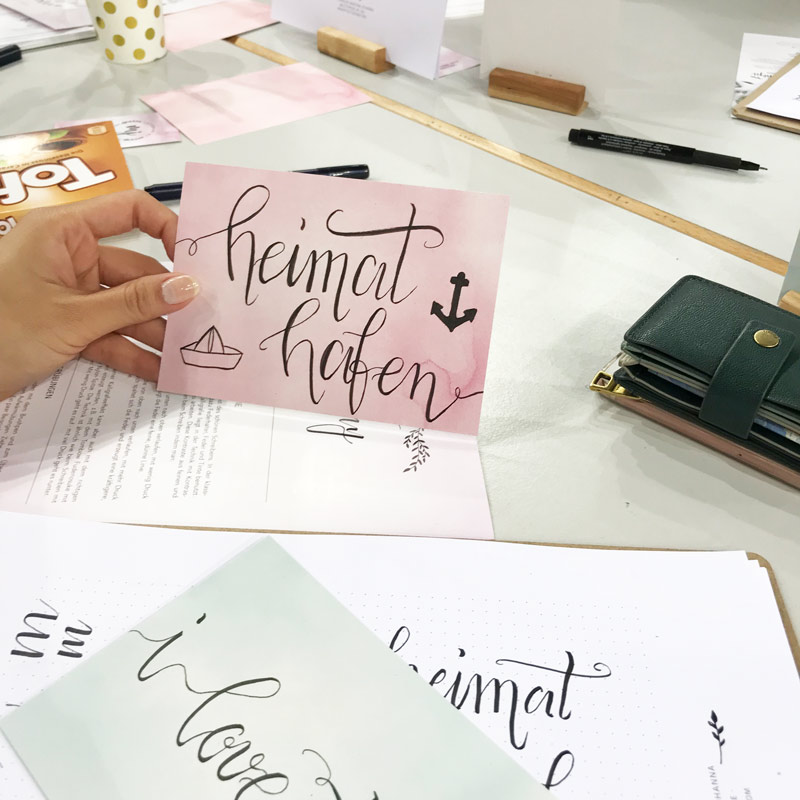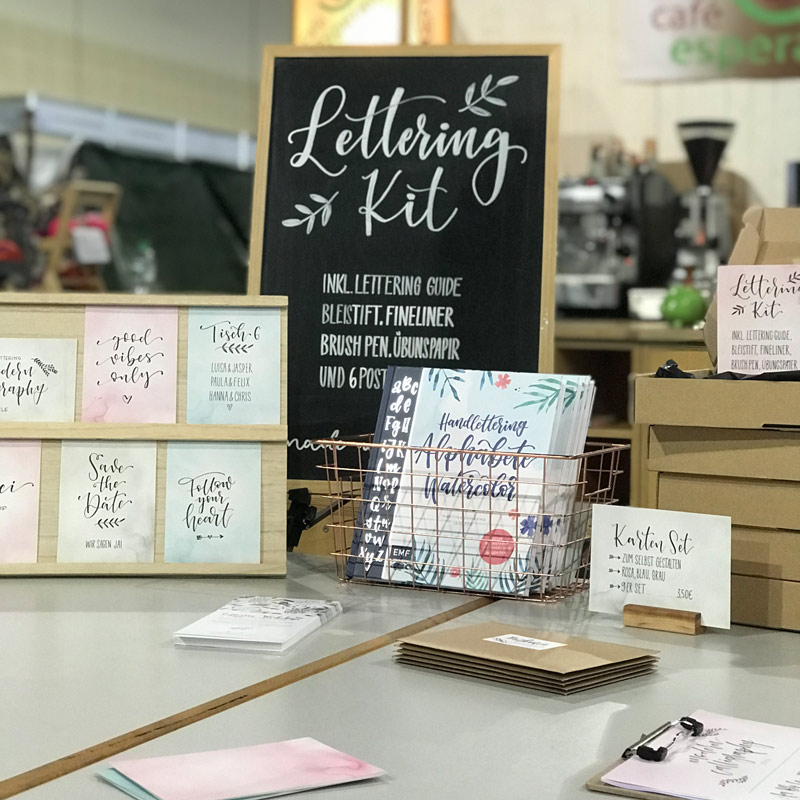
Lettering Workbook - Der Lettering Workshop für zuhause
Workbook – Moderne Kalligrafie mit dem Brushpen (Ausverkauft)
Brushlettering Workbook von Martina Johanna - Der Lettering Workshop für zuhause
Lettering by Martina Johanna - Workbook Moderne Kalligrafie mit dem Brushpen Brushlettering Workbook von A-Z
Workbook - Brush Lettering Workshop für zuhause
Der Lettering Workshop für zuhause
Für diejenigen, die in dieser Zeit kreativ werden möchten, biete ich ein Lettering Set für zuhause an. Das Workbook ist ein Lettering Workshop für zuhause rund um das Thema „Feine Buchstaben mit dem Brushpen“ und perfekt dazu geeignet, um zu lernen, zu üben und selber kreativ zu werden. Du bekommst es direkt mit passendem Brushpen und Karten Set nach Hause geliefert, um direkt loszulegen zu können.Das Lettering-Set für zuhause enthält:
A4 Workbook
Das Workbook enthält auf 24 Seiten Anleitungen, Buchstabenvorlagen sowie Tipps und Tricks rund um das Thema „Moderne Kalligrafie mit dem Brushpen“.
Brushpen
Der passende Tombow Fudenosuke Brushpen eignet sich mit seiner kleinen, flexiblen Spitze perfekt für einen feinen und zarten Look.
Karten-Set
Das Karten Set enthält insgesamt 9 Karten (3x rosa, 3x blau, 3x grau) mit zarten Aquarellhintergründen, die du selber gestalten kannst.
Mein Stand auf der Kreatibzeit in den Messehallen Bremen zum Thema Brushlettering, Moderne Calligraphy
Kreativzeit – Rückblick und Materialliste
Schön war es auf der Kreativzeit in den Messehallen Bremen. Drei Tage lang durfte ich dort kleine Schnupperkurse zum Thema „Brushlettering im modernen Kalligrafie Stil“ geben. Es war unglaublich aufregend und schön, so viele Menschen zu treffen, die Lust auf schöne Buchstaben haben getreu dem Motto: Endlich wieder schön schreiben!